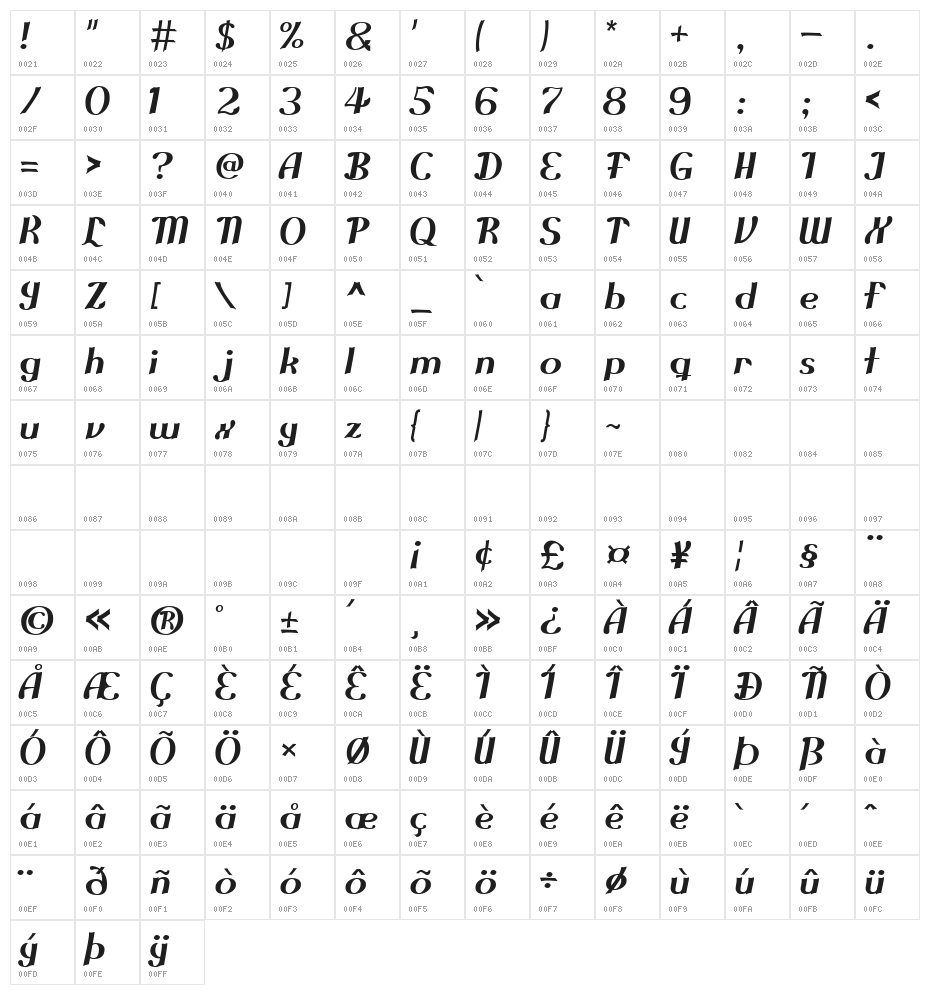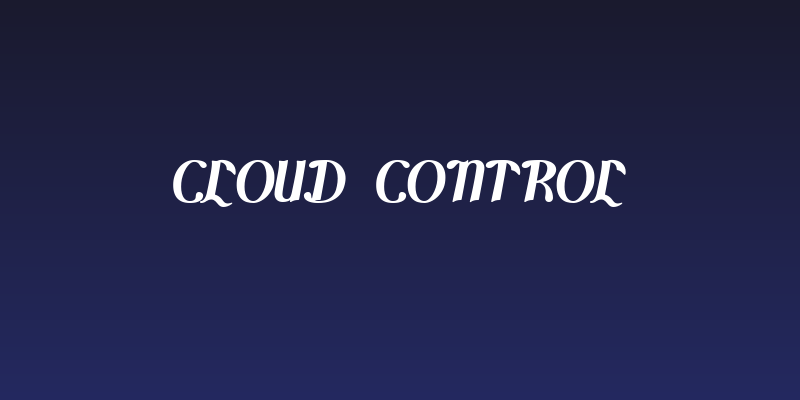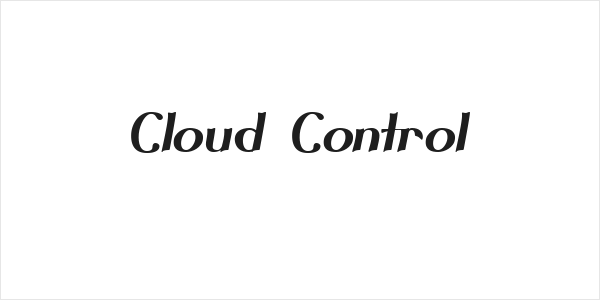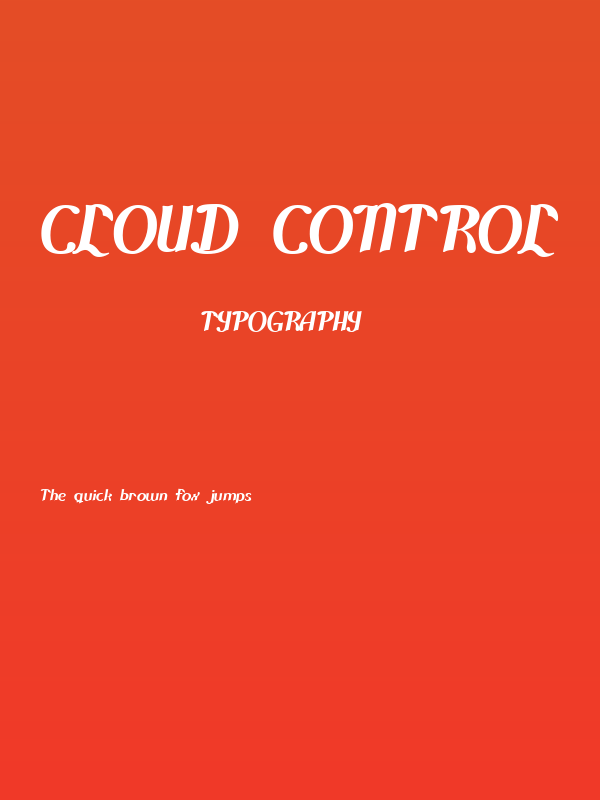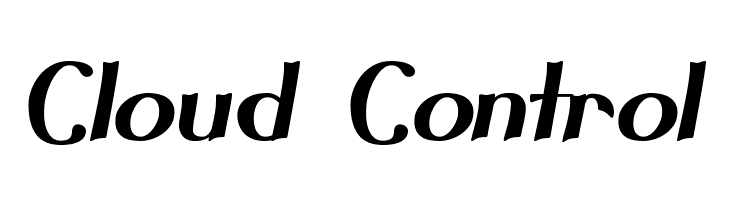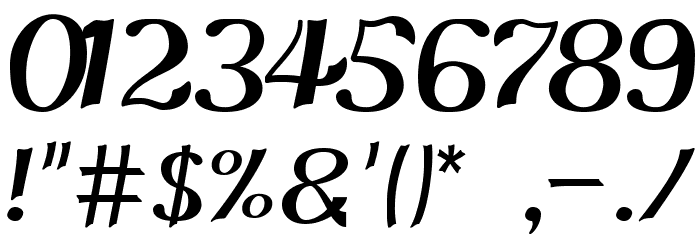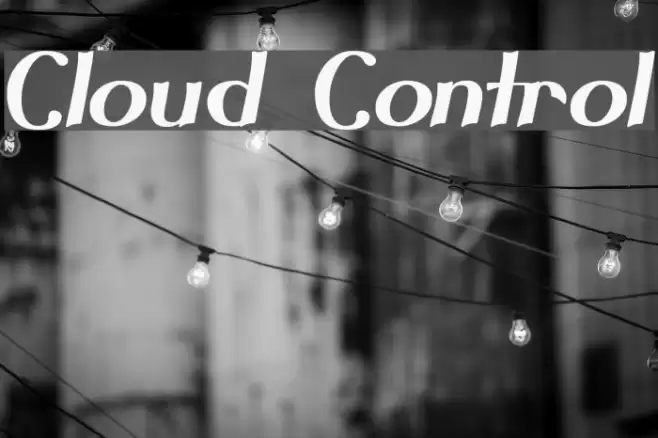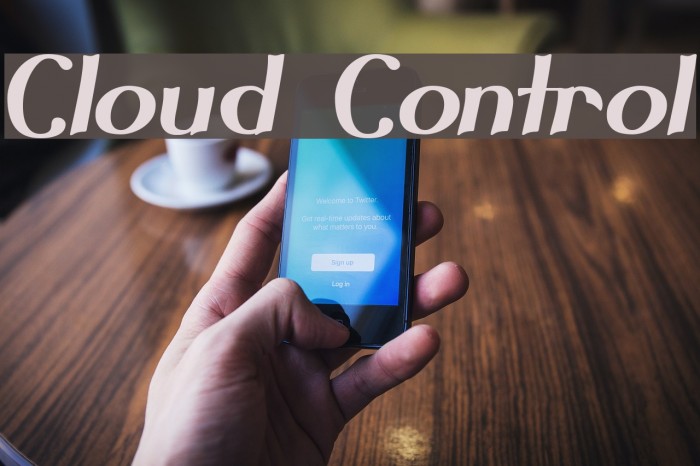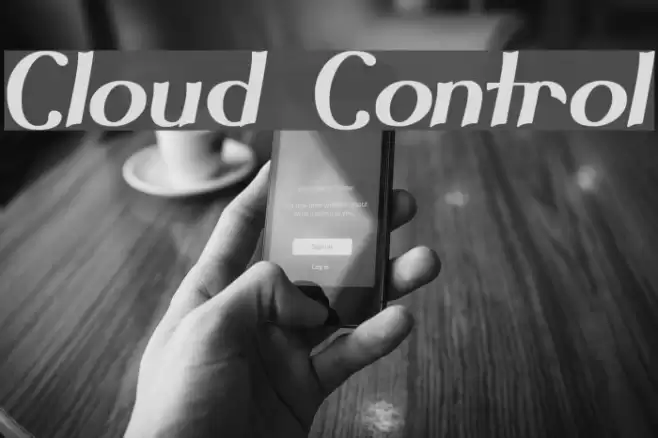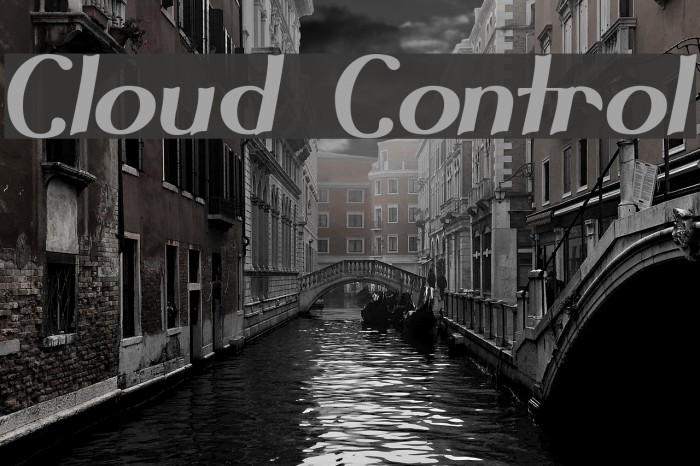
Cloud Control Font
✎ Script
| Anwendungsfall | Headlines, Logos, Branding |
| Vorgeschlagene Projekte | Ideal for branding, logos, headlines, and creative projects that require a bold and stylish script. |